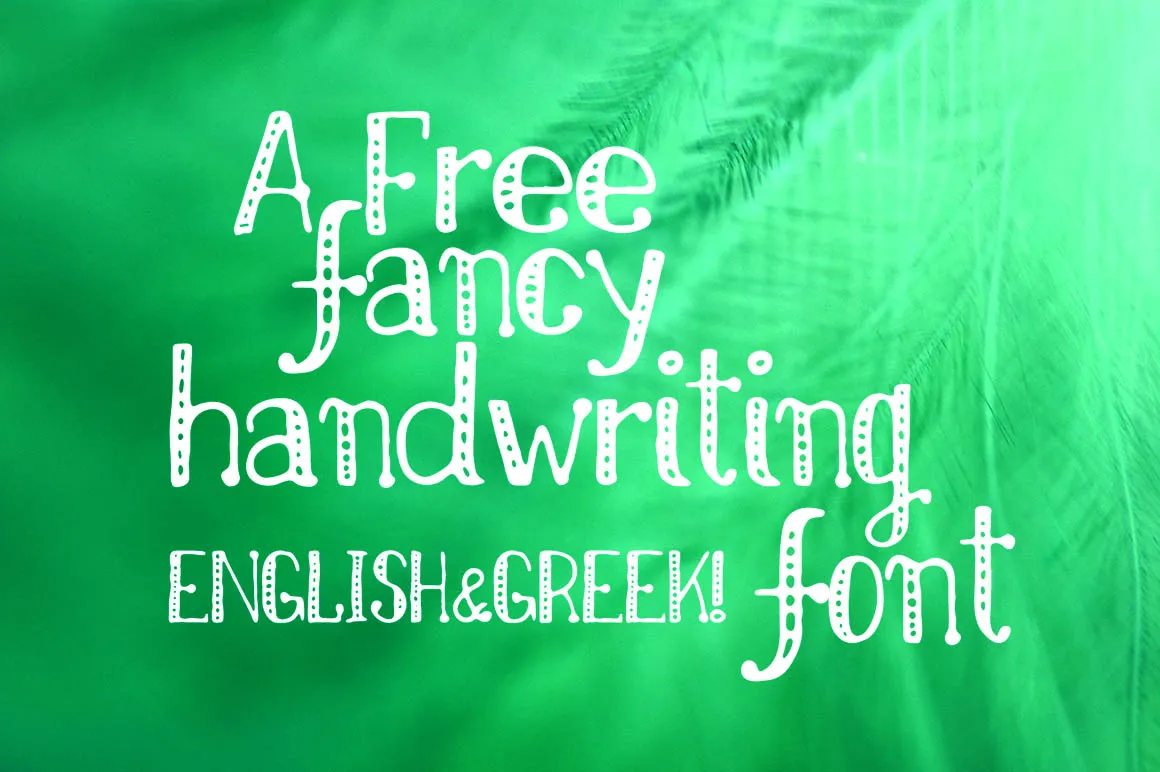
A Nikolidas Hand Font é uma elegante maneira de dar um toque pessoal a seus designs digitais. Ela foi criada pelo designer Hamilton e traz linhas finas e suaves, ideias perfeitas para aqueles projetos que precisam transmitir intimidade ou ser mais amigáveis aos olhos do leitor. Com seu traço cuidadosamente elaborado em estilo de mão escrita, esta fonte é ideal para o uso em aplicativos de email, postagens nas redes sociais e até mesmo materiais publicitários onde você quer que as mensagens falam diretamente com seus seguidores ou clientes. Ideal tanto para criar um design minimalista quanto para aqueles que buscam algo mais elaborado, a Nikolidas Hand Font ajuda a transmitir uma mensagem de forma elegante. Suas linhas delicadas e suaves se tornam perfeitas para expressar sua personalidade através da escrita digital, deixando seu trabalho com um toque autêntico que destaca seus conteúdos. Como qualquer outra fonte de estilo de mão, ela também pode ser usada para criar selos digitais ou assinaturas que traduzam a personalidade única do criador.